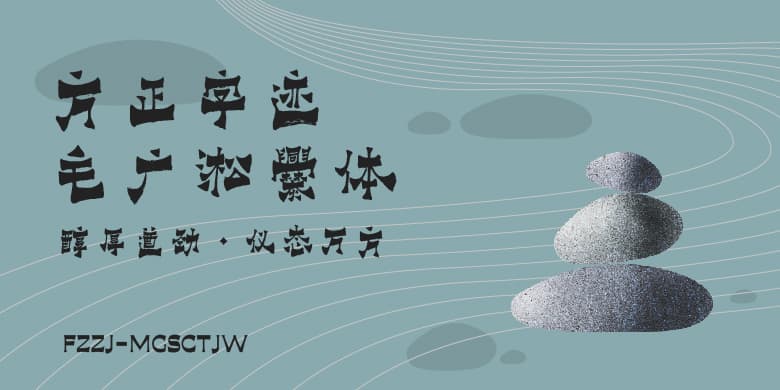
方正字迹-毛广淞爨体
方正字迹-毛广淞爨体,使用长锋羊毫毛笔书写,点画成三角造型,灵动虚实相生;横画两端上翘,成宽横大势,如千里阵云;撇、捺左右开张,运笔提顿极度夸张,收笔上扬,妙趣横生;竖画峻韧峭拔,力顶千钧。朴厚中透着灵动,刚健与柔媚共有,金石与书卷同存。典雅蕴籍,醇厚遒劲,仪态万方,极具庙堂壮美之景象。开创标题、榜书、匾额字体一代新风。
该字体风格是在立足魏晋书风基础之上,结合现代审美情趣所创立的极为优秀的新字体。毛爨体深得“二爨"端朴方劲,雄强古拙之风骨,峻逸旷远之神韵。运旷达胸襟于笔端,独出机杼,高妙奇特,浑然天成,彰显一派正大气象。
作者毛广淞,是中国书法家协会会员、中国书协书法培训中心教授、中国国际友好联络会理事、清华大学书画高研班导师、对外经贸大学研究生文化艺术导师。曾被评为“中国书法十大年度人物”。“毛广淞爨体书法”受到国家版权局版权登记保护。